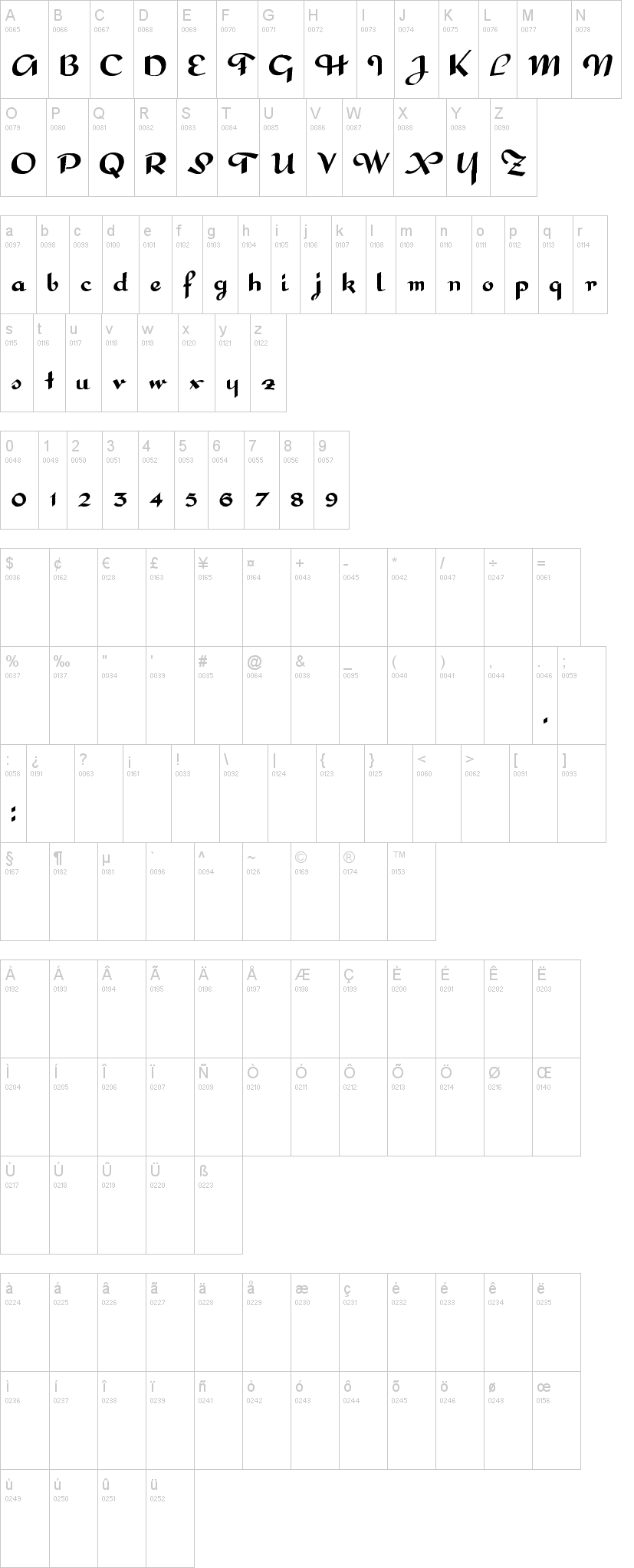
Interdite Script 是一款拥有精致装饰设计的脚本字体,设计师将细节处理得非常精细,使得这款字体具有独特的外观效果。它的设计灵感来自经典的古典文字,以及现代的脚本字体,使它具有非常精致的外观。Interdite Script的字体设计特别适合用于海报、标志、品牌标识等等,它能够给你的设计带来非常棒的效果。内容介绍
Interdite Script是一款非常不错的手写艺术字体,具有很好的视觉感,适合于文化类的宣传设计、商业类品牌的广告和产品包装设计以及个性化文字排版等较多场景。